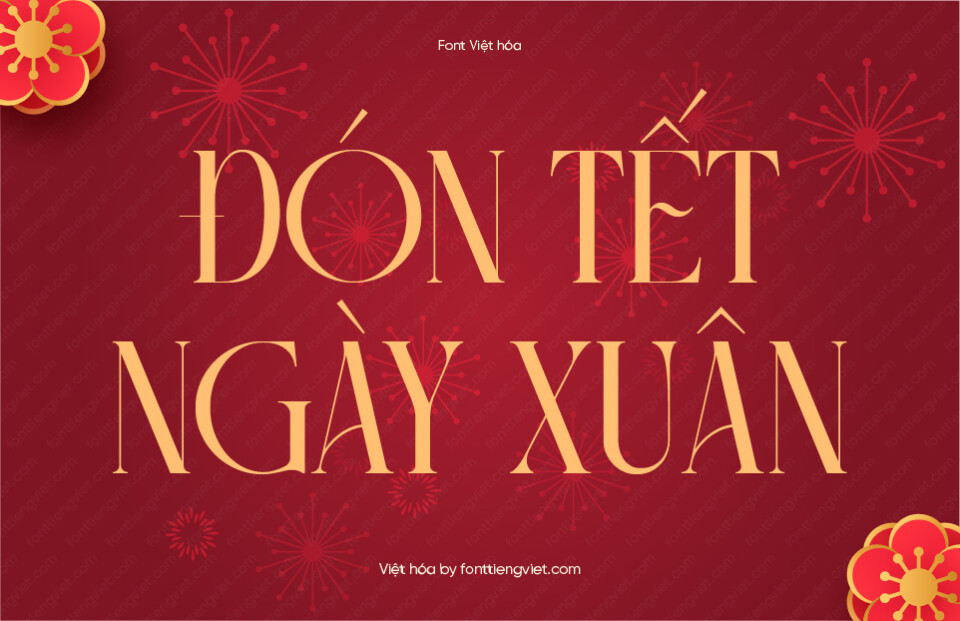
Font Việt hóa 1FTV VIP Glamora – Font tết
Giới thiệu bộ Font Việt hóa 1FTV VIP Glamora – Font tết
Chào đón không khí rộn ràng của những ngày cuối năm, nhu cầu tìm kiếm các mẫu thiết kế mang âm hưởng truyền thống nhưng vẫn hiện đại đang trở nên cực kỳ sôi động. Trong số các tài nguyên thiết kế nổi bật, Font Việt hóa 1FTV VIP Glamora – Font tết chính là lựa chọn hàng đầu cho những ai muốn thổi hồn vào các tác phẩm của mình. Đây là một bộ Font Miễn Phí chất lượng cao, được tinh chỉnh kỹ lưỡng để phục vụ riêng cho thị trường Việt Nam. Với những đường nét thanh mảnh, uốn lượn mềm mại, bộ font này không chỉ mang lại vẻ đẹp sang trọng mà còn gợi nhắc về sự may mắn và tài lộc. Việc sử dụng Font Việt hóa 1FTV VIP Glamora – Font tết giúp các designer dễ dàng tạo ra những sản phẩm chuyên nghiệp mà không lo lỗi font hay thiếu dấu tiếng Việt, đảm bảo tính thẩm mỹ cao nhất cho mọi dự án đồ họa.
Đặc điểm nổi bật của Font Việt hóa 1FTV VIP Glamora – Font tết
Bộ Font Việt hóa 1FTV VIP Glamora – Font tết sở hữu phong cách Serif hiện đại kết hợp với những chi tiết cách điệu đầy nghệ thuật. Điểm mạnh lớn nhất của nó là khả năng hiển thị tiếng Việt hoàn hảo, từ các dấu thanh cho đến các ký tự đặc biệt đều được căn chỉnh đồng nhất. Cấu trúc chữ của Font Việt hóa 1FTV VIP Glamora – Font tết mang hơi hướng của sự thịnh vượng, rất phù hợp để làm tiêu đề bài viết, thiết kế bìa tạp chí hoặc các ấn phẩm quảng cáo cao cấp. Bên cạnh đó, độ tương phản giữa các nét thanh và nét đậm được thiết kế vô cùng tinh tế, giúp tạo nên chiều sâu không gian cho bản thiết kế. Dù bạn sử dụng trên các nền tảng kỹ thuật số hay in ấn trực tiếp lên chất liệu giấy, bộ font này vẫn giữ được độ sắc nét và sự lôi cuốn vốn có, khẳng định đẳng cấp của người sử dụng trong mắt khách hàng và đối tác.
Ứng dụng thực tế của Font Việt hóa 1FTV VIP Glamora – Font tết
Ứng dụng của Font Việt hóa 1FTV VIP Glamora – Font tết rất đa dạng, đặc biệt là trong các chiến dịch truyền thông dịp lễ hội. Bạn có thể sử dụng bộ chữ này để thiết kế thiệp chúc mừng năm mới, bao lì xì, hay các banner quảng cáo sự kiện tri ân khách hàng. Trong lĩnh vực giáo dục, các bạn học sinh và giáo viên cũng có thể dùng Font Việt hóa 1FTV VIP Glamora – Font tết để làm báo tường, trang trí slide bài giảng hoặc thiệp mời họp lớp, tạo nên không khí ấm cúng và trang trọng. Hơn thế nữa, đối với những người làm thương hiệu, việc lồng ghép Font Việt hóa 1FTV VIP Glamora – Font tết vào logo hoặc bao bì sản phẩm quà tặng Tết sẽ giúp gia tăng giá trị nhận diện thương hiệu một cách hiệu quả. Khả năng tùy biến linh hoạt giúp font chữ này thích nghi tốt với nhiều gam màu nóng như đỏ, vàng, cam – những màu sắc chủ đạo của ngày Tết cổ truyền Việt Nam, mang lại cảm giác vui tươi và tràn đầy năng lượng tích cực cho người xem.
Cách sử dụng Font Việt hóa 1FTV VIP Glamora – Font tết hiệu quả
Để phát huy tối đa vẻ đẹp của Font Việt hóa 1FTV VIP Glamora – Font tết, người thiết kế nên kết hợp nó với các font chữ không chân (Sans-serif) đơn giản ở phần nội dung phụ. Điều này giúp tạo ra sự cân bằng thị giác, khiến tiêu đề chính trở nên nổi bật và dễ đọc hơn. Ngoài ra, việc tận dụng các ký tự thay thế (alternates) trong bộ Font Việt hóa 1FTV VIP Glamora – Font tết sẽ giúp bạn tạo ra những biến tấu độc đáo, không đụng hàng cho từng sản phẩm cụ thể. Hãy chú ý đến khoảng cách giữa các chữ cái (kerning) để đảm bảo văn bản luôn hài hòa và chuyên nghiệp. Đối với các bài đăng trên mạng xã hội, sử dụng Font Việt hóa 1FTV VIP Glamora – Font tết kèm theo các hiệu ứng đổ bóng hoặc viền kim loại sẽ làm cho thông điệp của bạn trở nên thu hút và bắt mắt hơn bao giờ hết, dễ dàng chiếm trọn cảm tình của cộng đồng mạng ngay từ cái nhìn đầu tiên.
Kết luận về Font Việt hóa 1FTV VIP Glamora – Font tết
Hy vọng rằng bộ Font Việt hóa 1FTV VIP Glamora – Font tết sẽ trở thành người bạn đồng hành đắc lực cho các dự án sáng tạo của bạn trong mùa lễ hội năm nay. Với sự kết hợp hoàn hảo giữa tính truyền thống và nét hiện đại, đây chắc chắn là một tài nguyên không thể thiếu trong thư viện của các nhà thiết kế. Hãy nhanh tay tải ngay và trải nghiệm sự khác biệt mà bộ font này mang lại cho các sản phẩm nghệ thuật của mình. Đừng quên truy cập vào Font Miễn Phí, Font Việt Hóa, Font Việt hóa 1FTV VIP Glamora – Font tết thường xuyên để cập nhật thêm nhiều mẫu chữ độc đáo và miễn phí khác. Chúc bạn có những tác phẩm thiết kế thật ấn tượng và một năm mới an khang, thịnh vượng cùng với sự hỗ trợ đắc lực từ Font Việt hóa 1FTV VIP Glamora – Font tết.